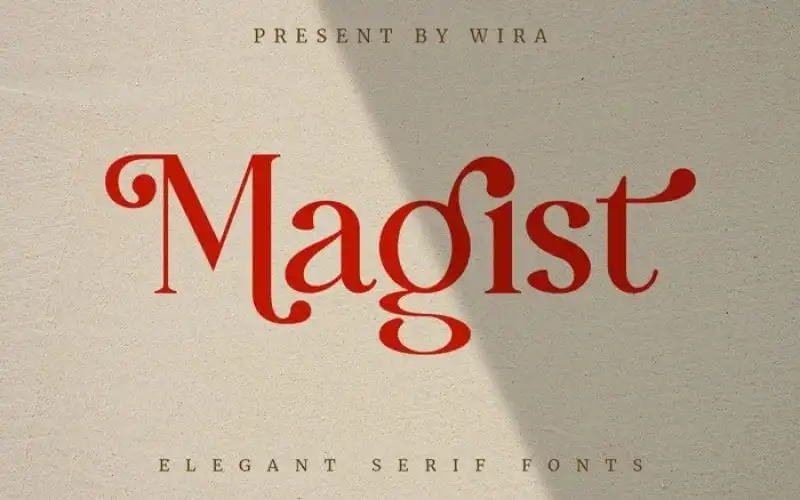
Magist Serif Font – Fonte Grátis
Magist Serif Font
Magist Serif é uma elegante fonte serif que traz aos seus projetos um toque sofisticado e aprimorado. Esta fonte foi criada por Wirastudio, um talentoso designer de fontes, e é rica em alternativas de letras e ligaturas que permitem criar logotipos, postagens, imagens para blogs, projetos de marca, cartões de visita para casamentos e muito mais. Com seu estilo minimalista e elegante, Magist Serif oferece um leque ilimitado de opções para qualquer projeto gráfico em que seja necessário usar uma fonte serif. Seja você criando o próximo post do blog ou estilizando as cartas enviadas a convidados para um casamento, este é o tipo certo de trazer sua mensagem ao topo. Com Magist Serif, suas criações deixam um profundo impacto e são certamente uma escolha perfeita para qualquer projeto que você possa imaginar.